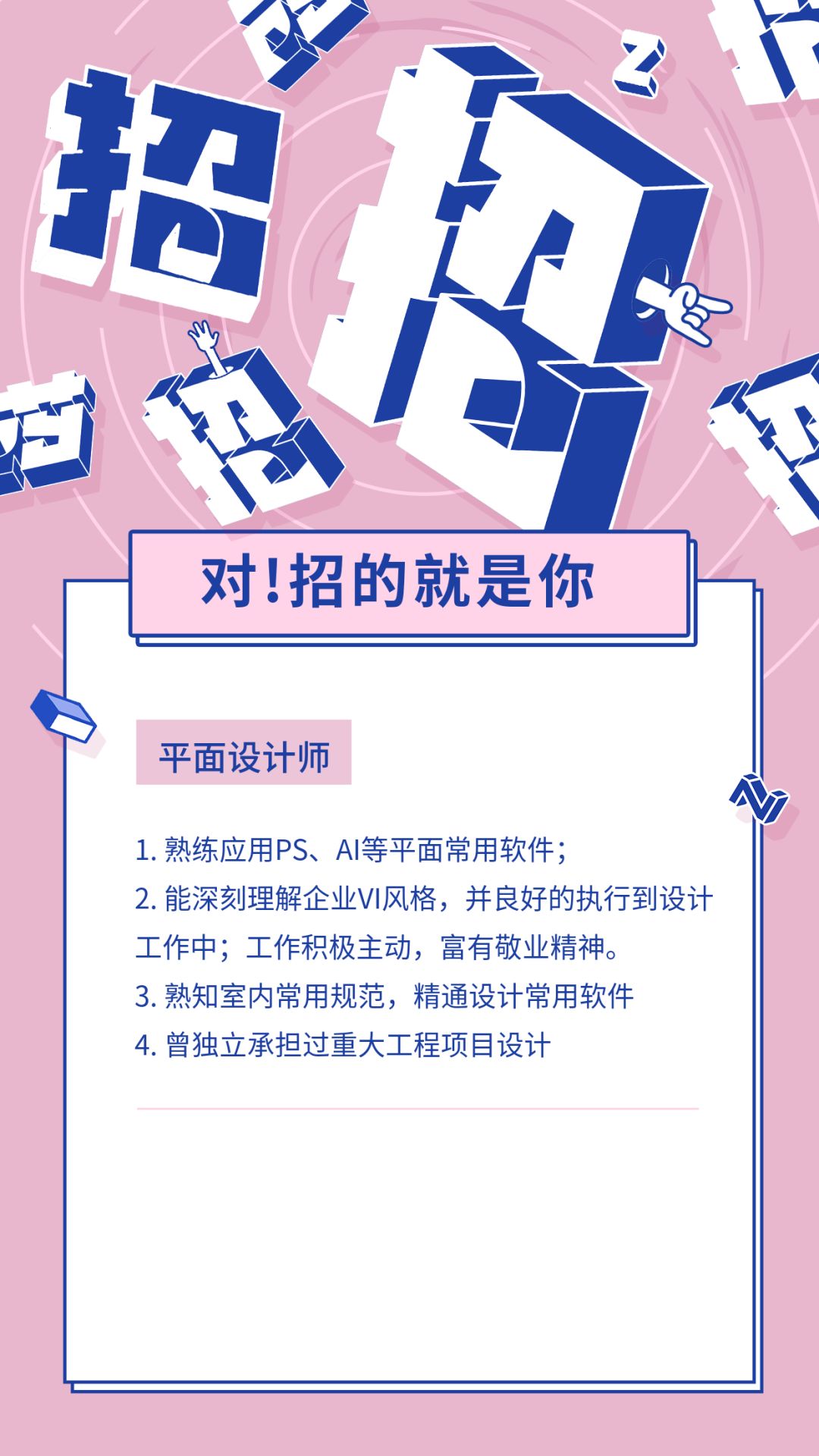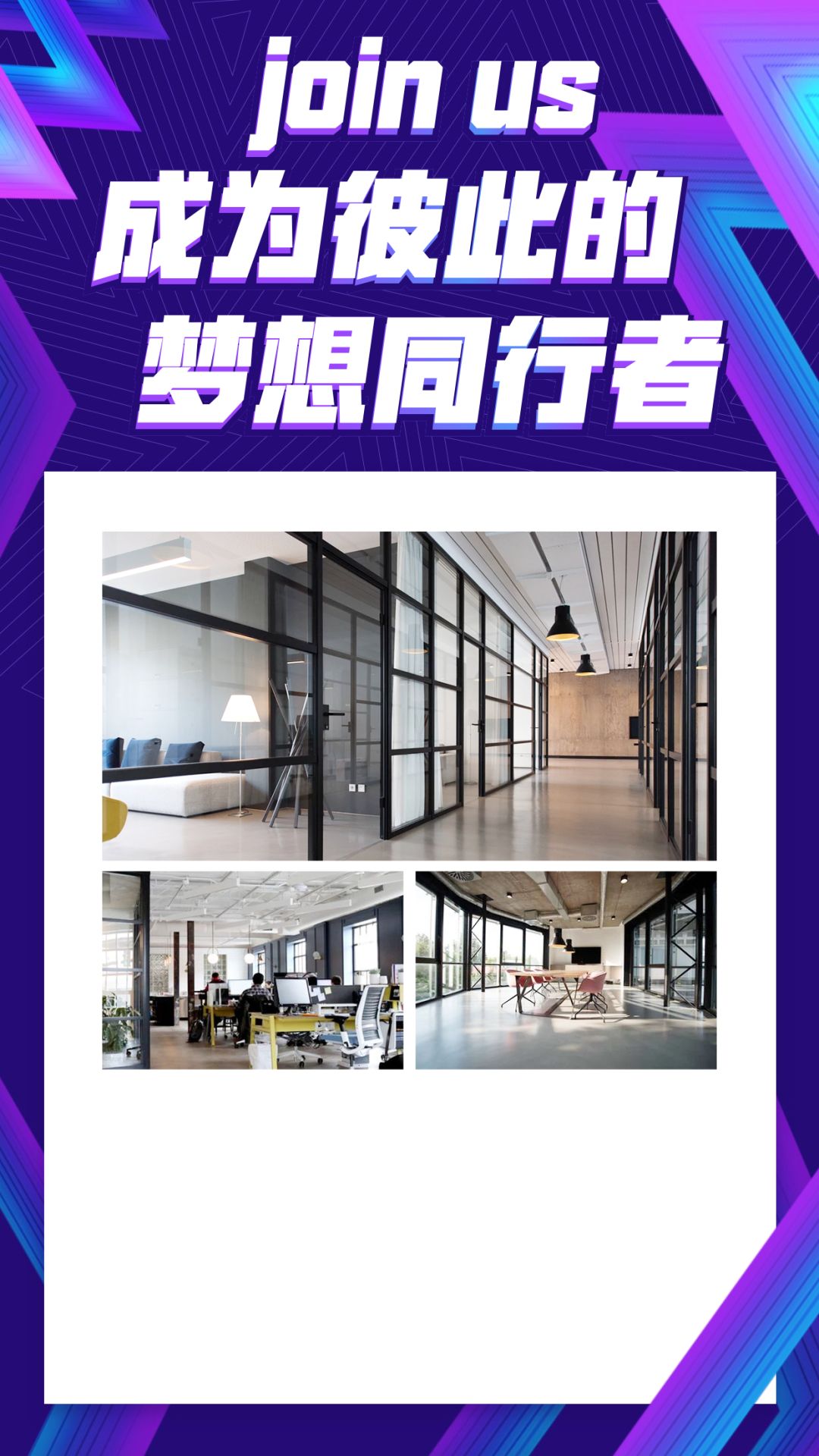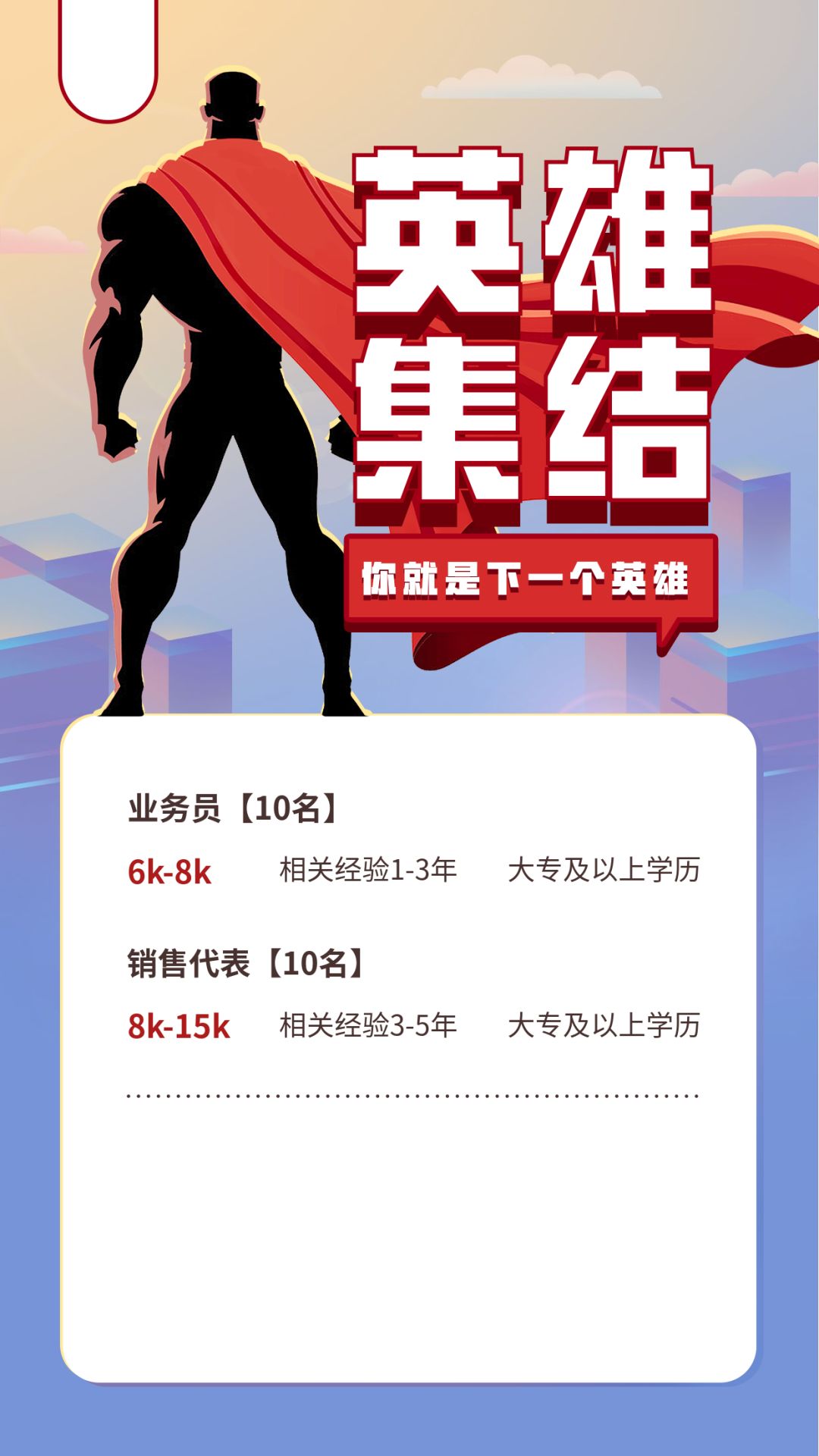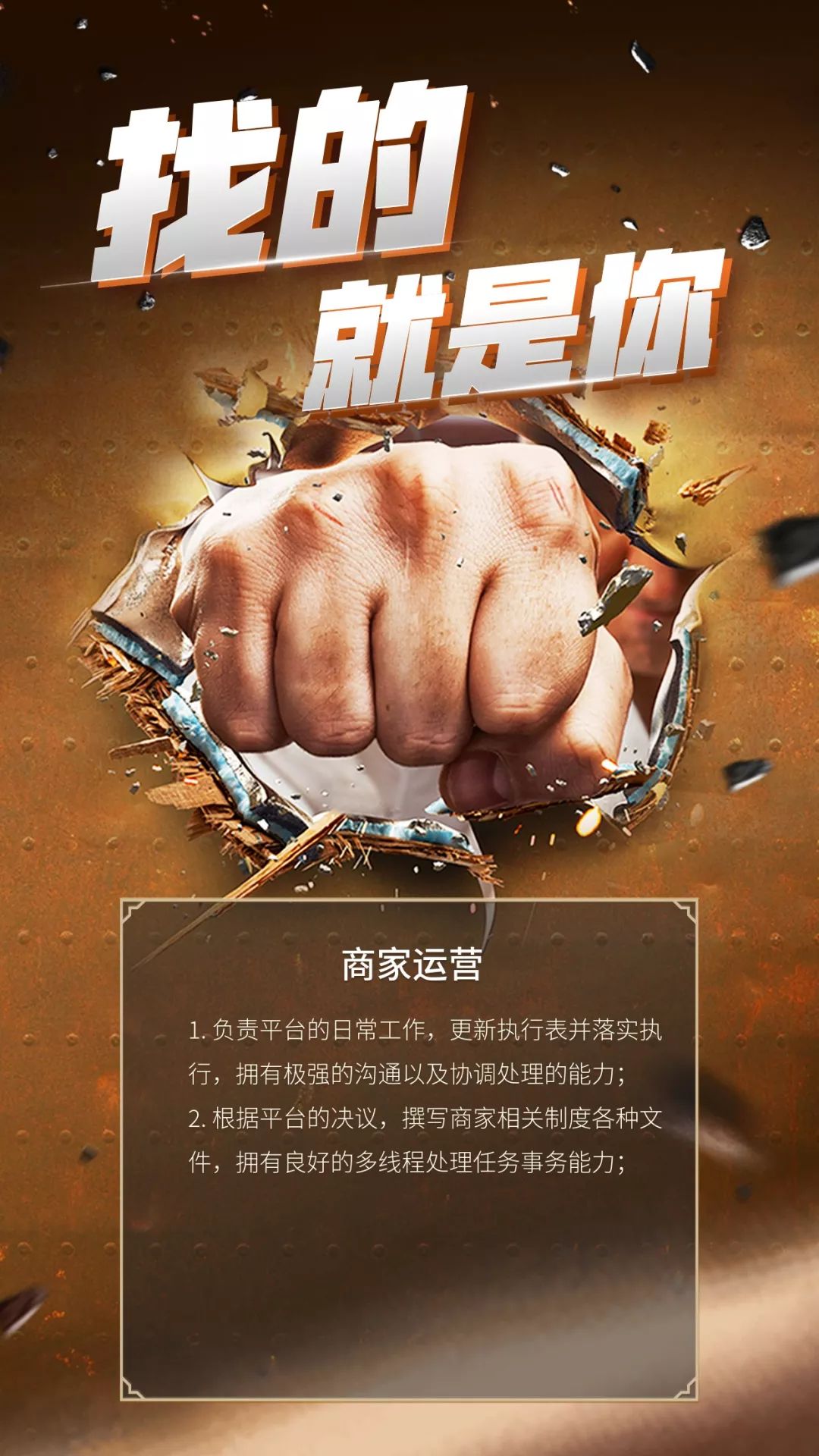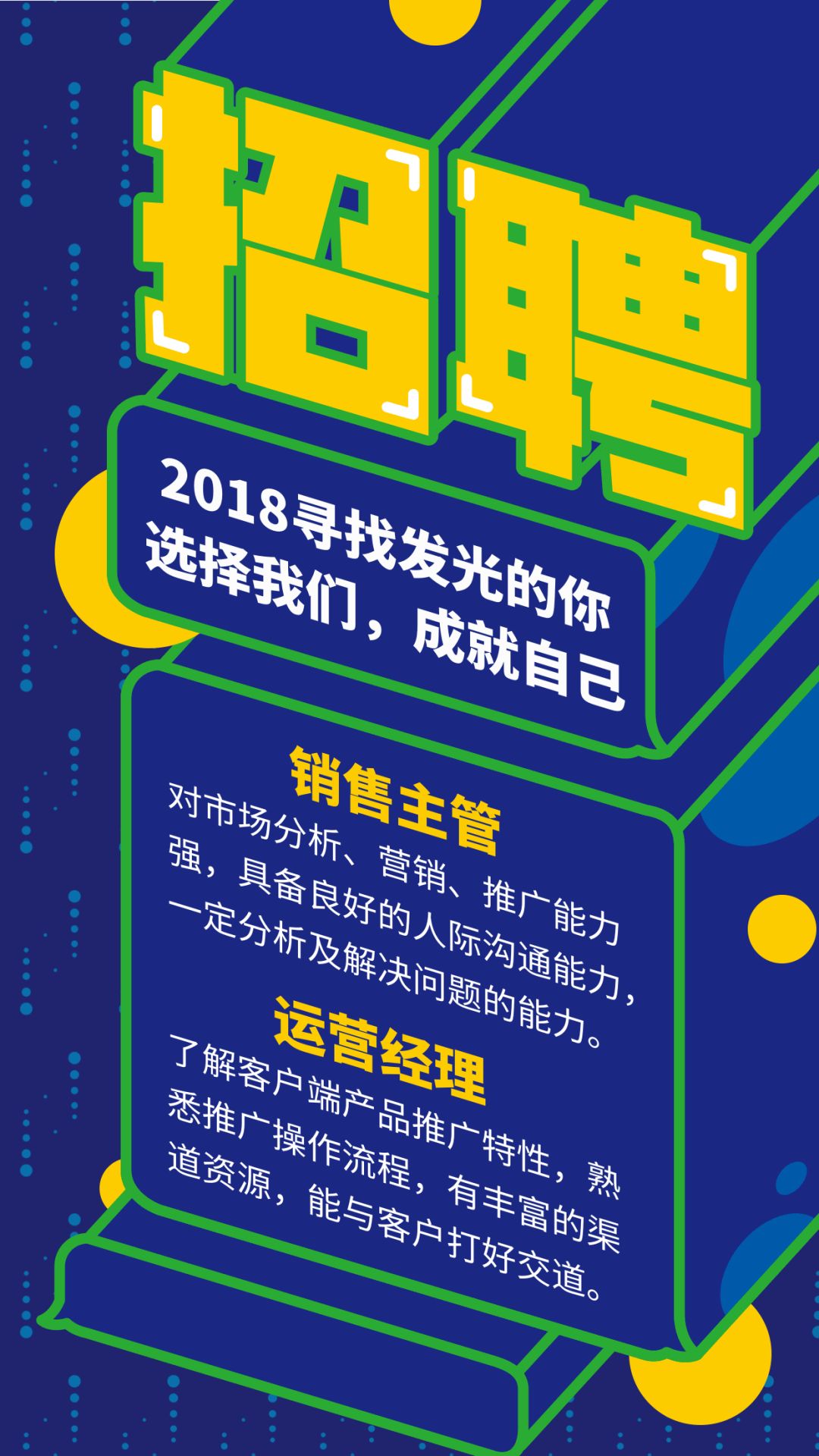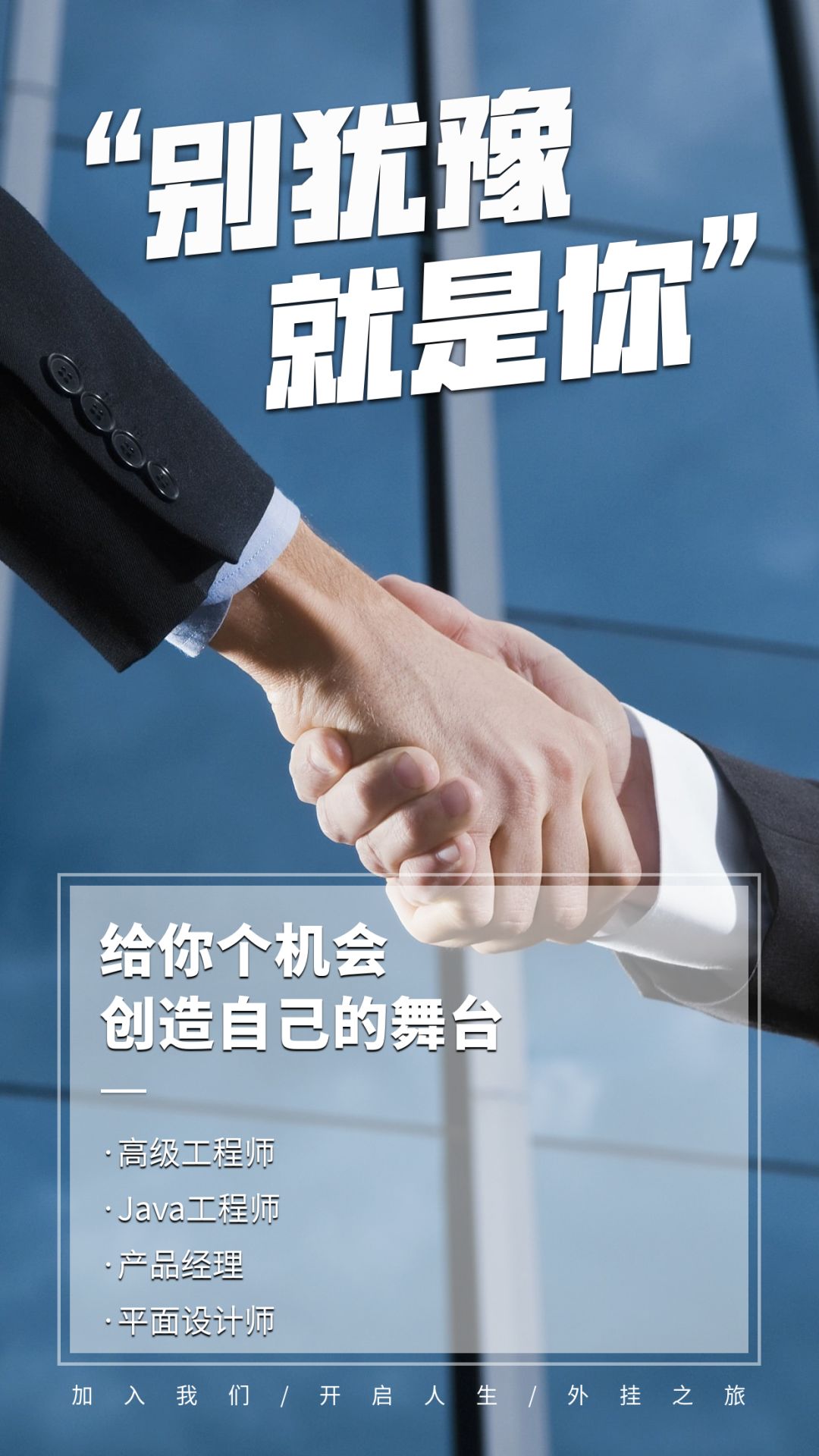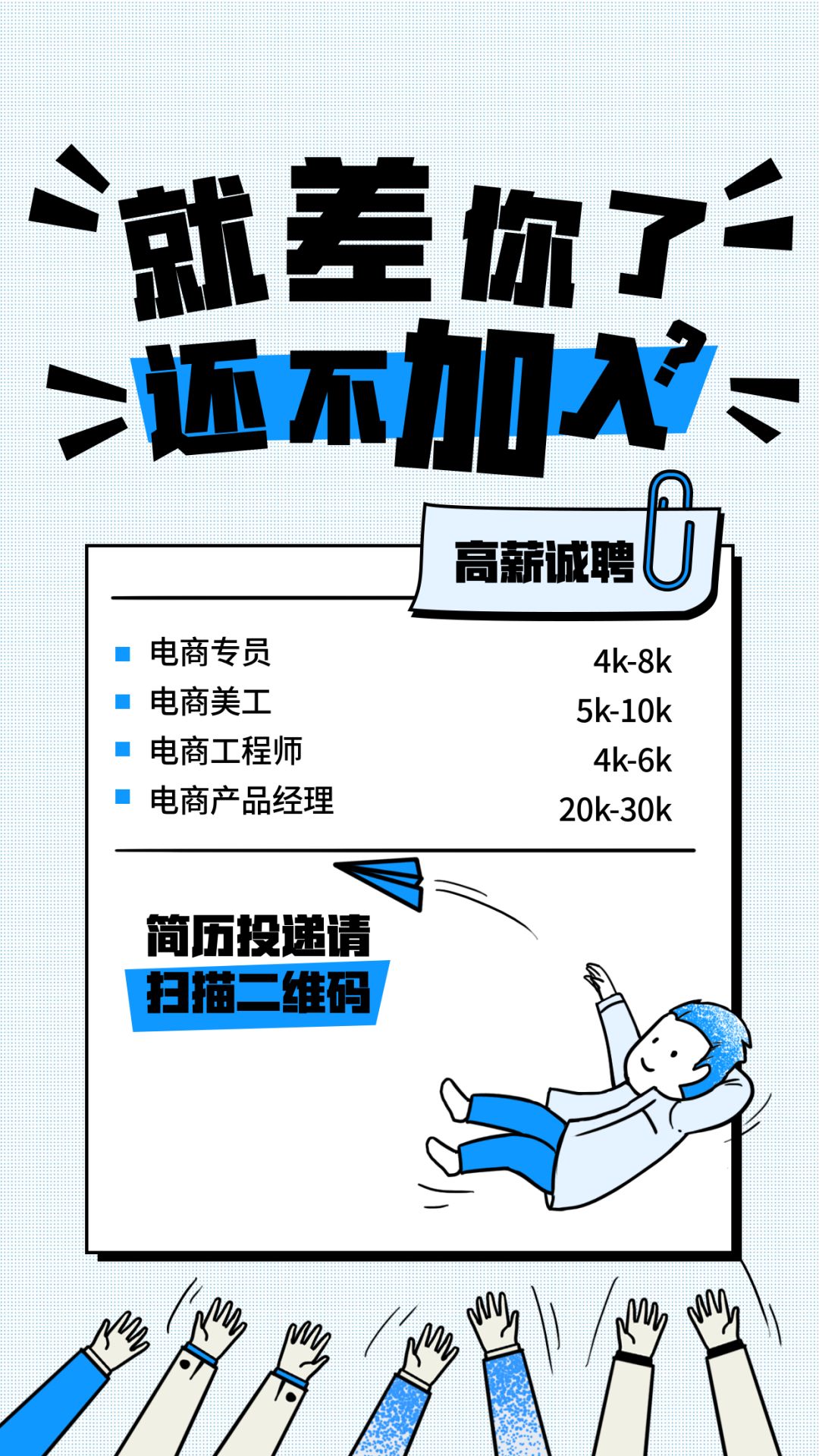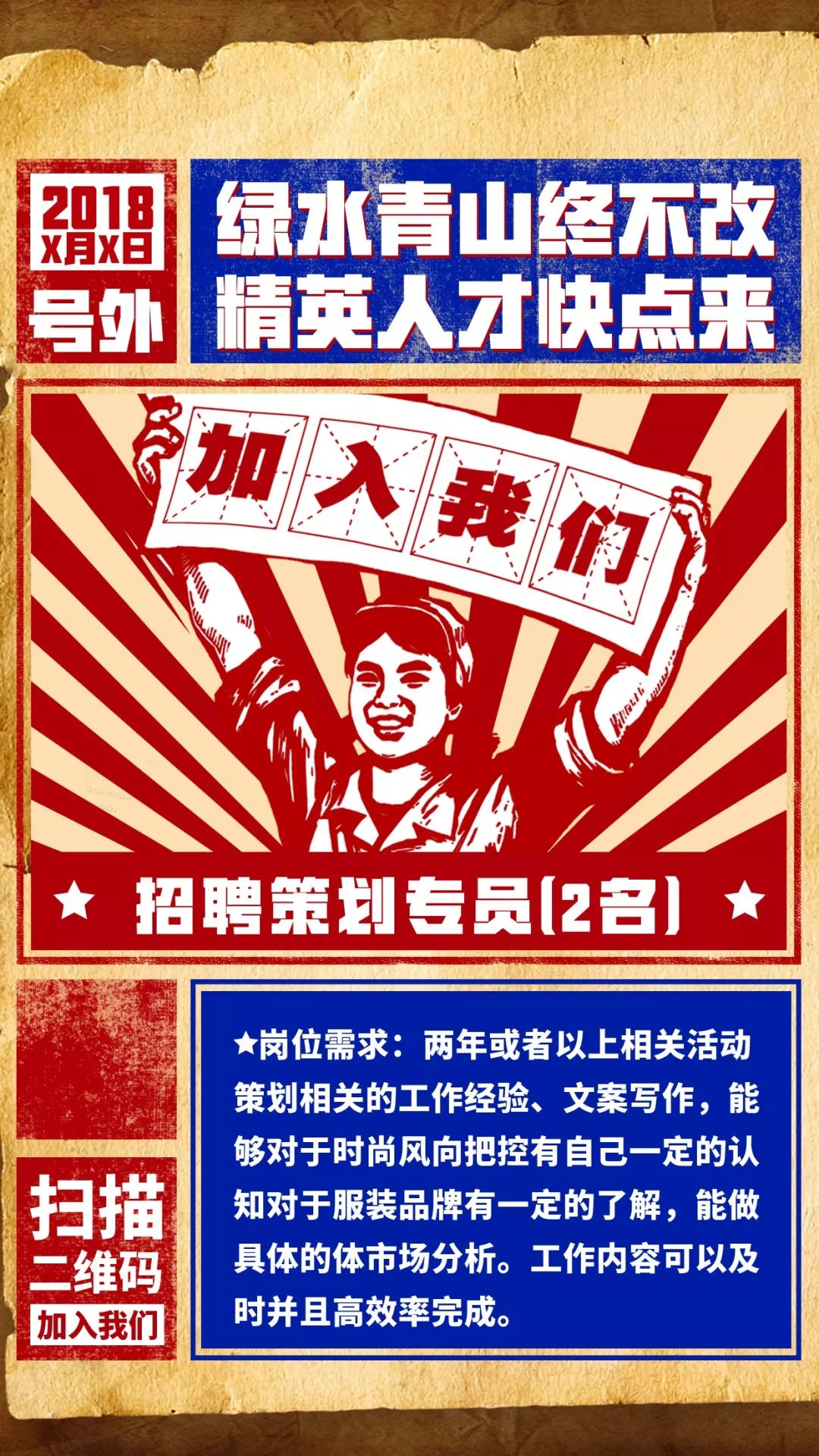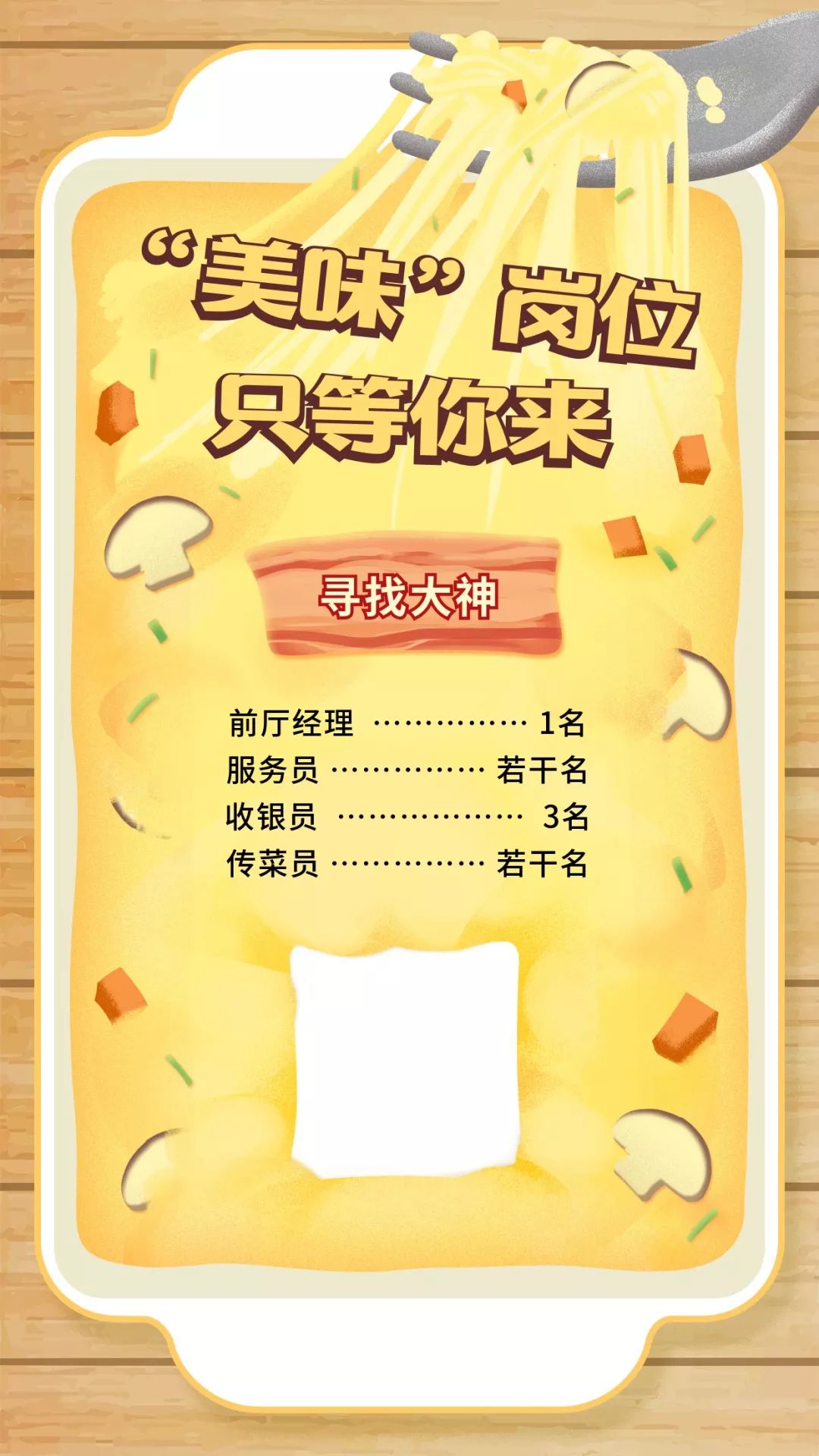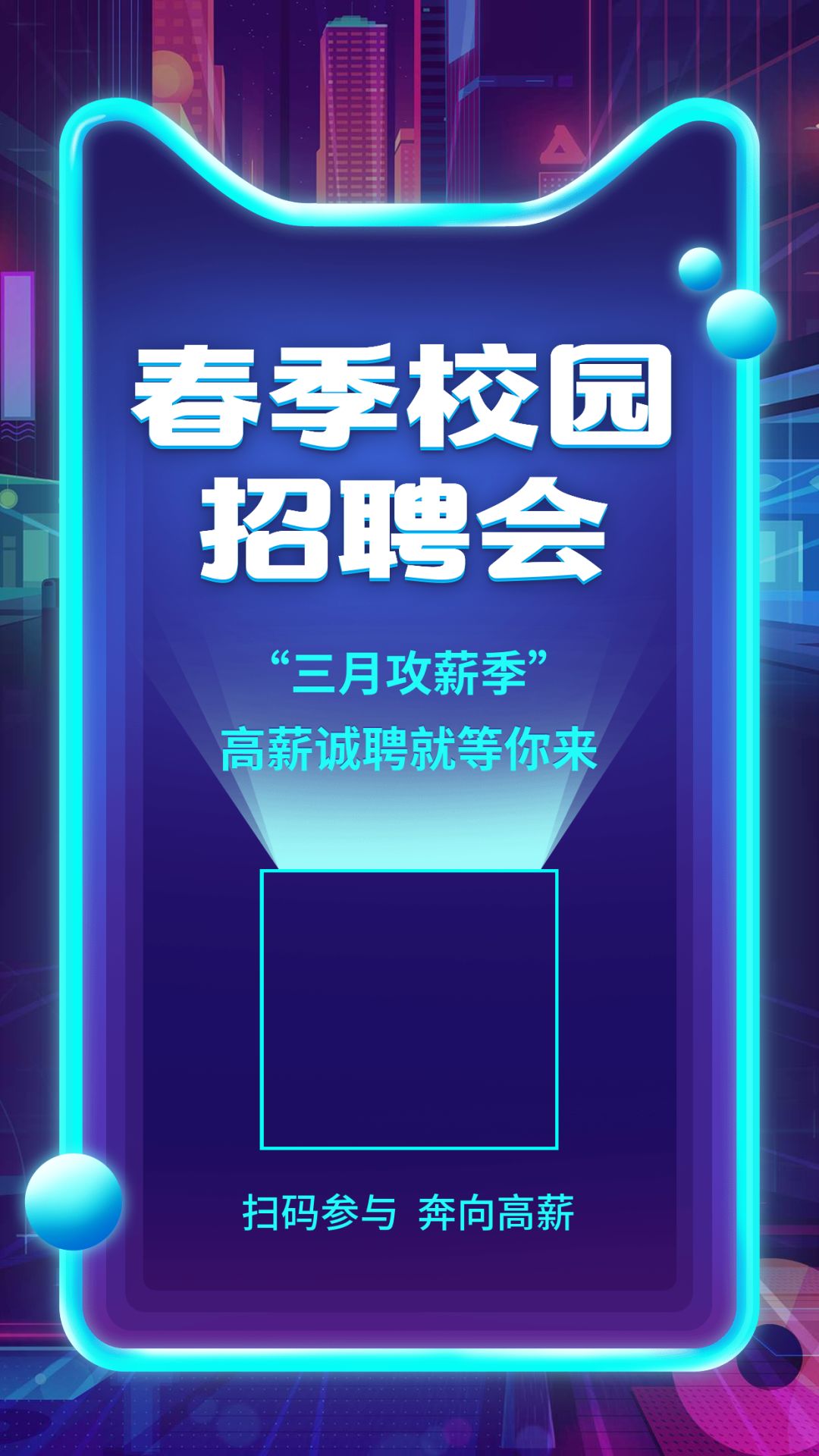
金三银四招(找)它难,先问问“颜值”能打几分?
最近赶上金三银四,求职招聘应该异常火爆才对,可还是有人抱怨,“找不到合适的人”,“都接不到几个靠谱的电话”,想过原因在哪吗?
招聘没诚意
都什么时代了,还打算以大段的文字取胜,你又不是大明星,谁看你啊!何况现在人都懒,谁愿意给你复制,然后手动转发?
这个倒是把文字做成图了,但黑压压的一片,你会有耐心一点点看下去吗?
终于有图了,至少知道公司是做什么的了,但还是不够用心。看看下面这些,都是我从官网案例里扒过来的~
汉仪力量黑
扑面而来的一种霸气、有实力的感觉,招人我们是认真的!
汉仪晓波敦黑
这款字体没力量黑那么刚,有点圆滑,看起来很有辨识度,像志玲姐姐一样,温柔地向你“开炮”!
庞门正道标题体
跟敦黑有点像,也是降低了身高,但人家棱角多多了,还是免费商用哦~
上面三款字体是最有招人缘的,求职者一看到就会挪不开眼,但也有一些性格奇特的“喵系”、“旺系”90后、00后,想吸引他们,就得靠哄~
▲汉仪铸字童年体
▲汉仪喵魂体
▲汉仪小麦体
▲汉仪趣黑
▲汉仪劲楷
▲站酷庆科黄油体
简历不用心
一不小心招聘说多了,下面说说求职者关心的。其实说白了招聘求职,就是买卖市场,买方使劲吆喝,卖方也得拿出看家本事,把面子工程要做到位。别整那些老掉牙的传统表格,我要是hr,直接丢垃圾桶……
就算你内容写得再用心,再详尽,who care?我们要的是第一印象,舒服、整洁、有重点!
▲汉仪铸字童年体